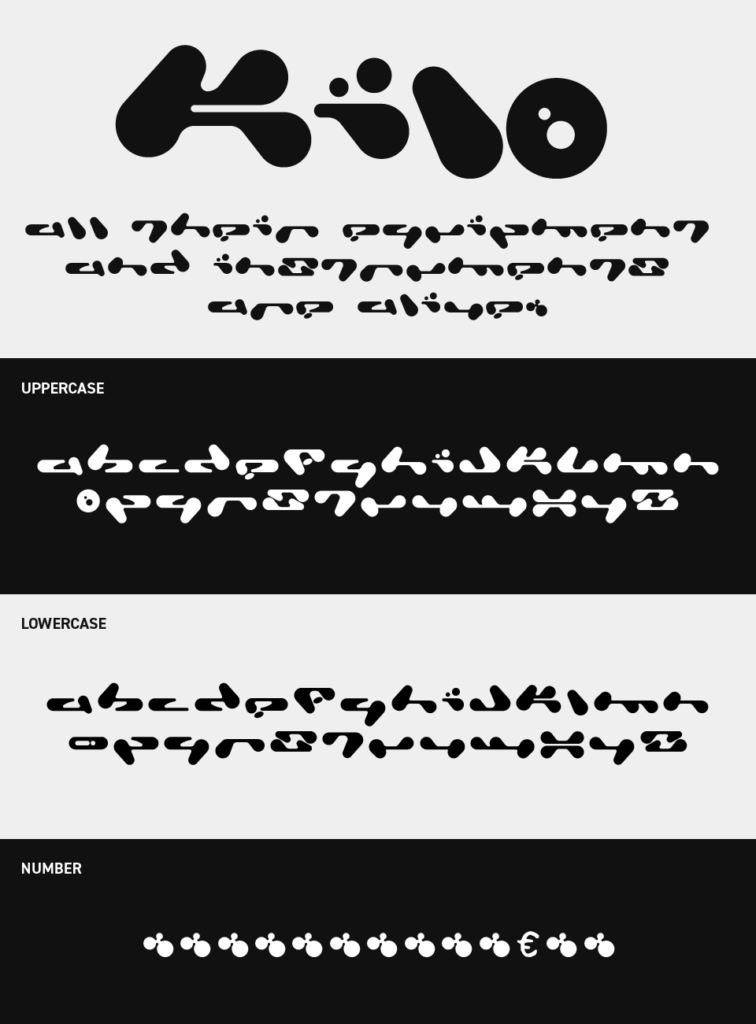
Kilo Font
Kiloフォントは、記号のように再構成されたユニークな字形が目を引く、Y2Kぽさもあり未来感もあるデザインフォントです。
文字というよりシンボルに近い造形で、既存のタイポグラフィでは出せない新鮮さがあり、アート性の高い表現に向いたフォントです。
丸や点、流れるような接続パーツがリズムを生み、文字列全体がひとつのグラフィック作品のように見えるフォントです。